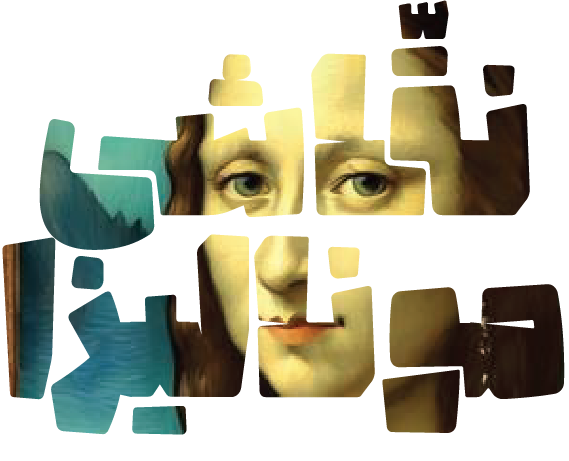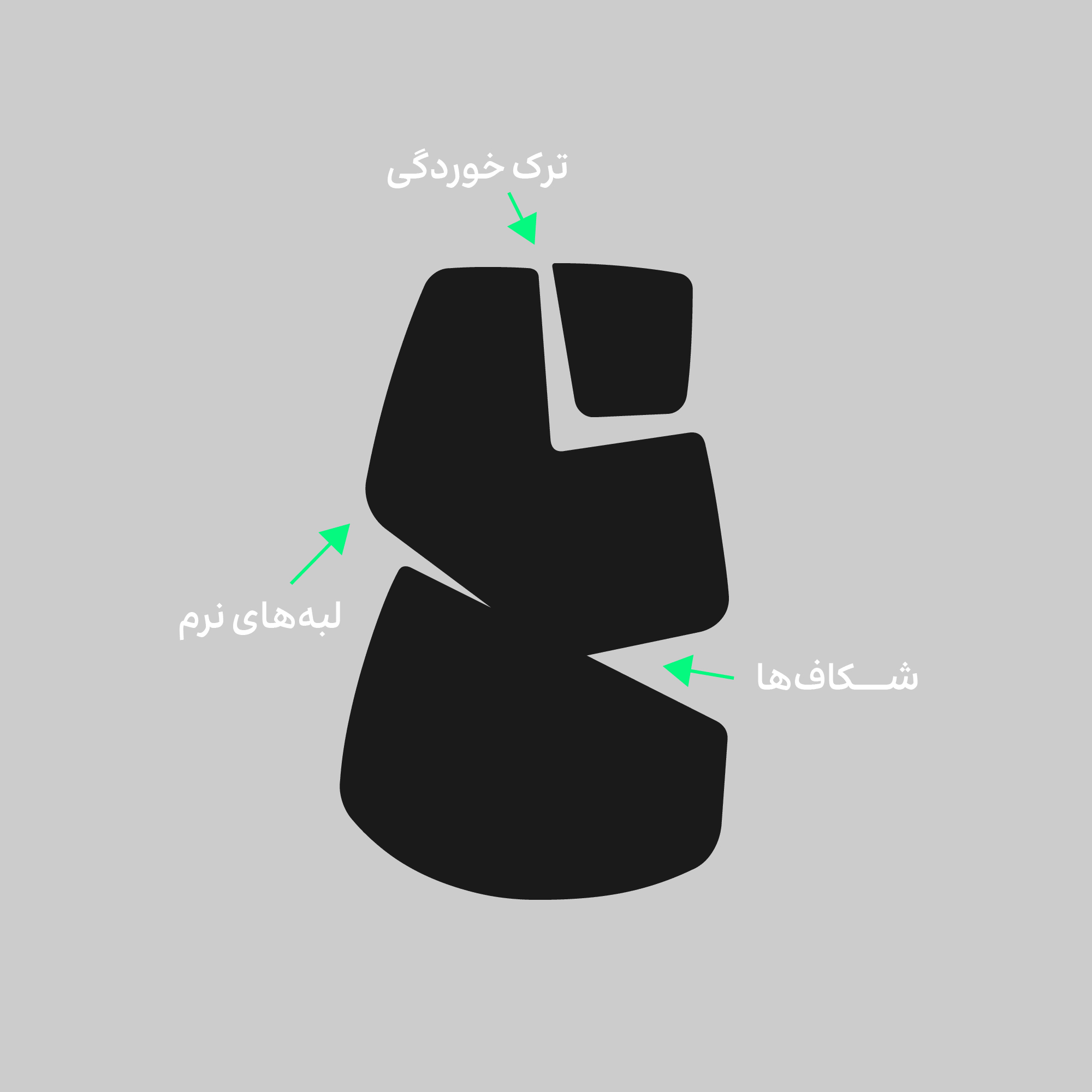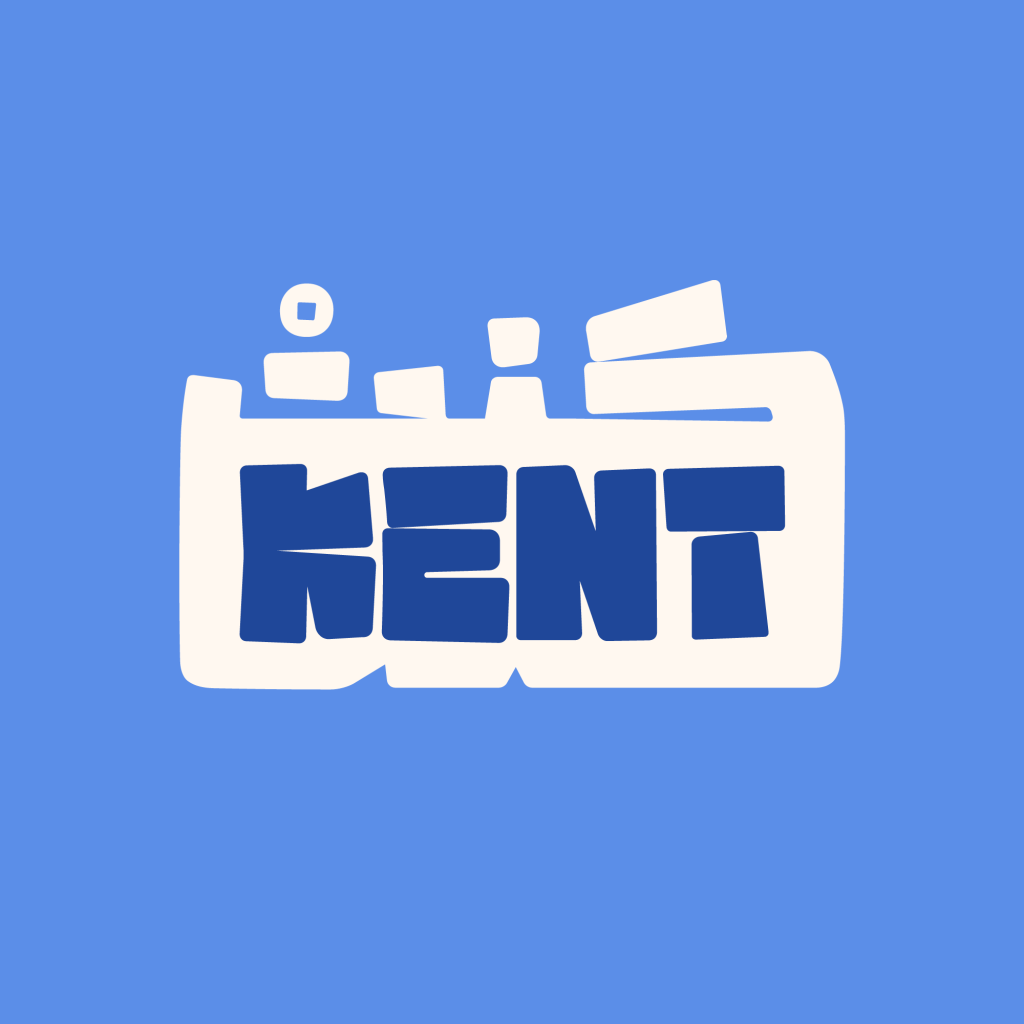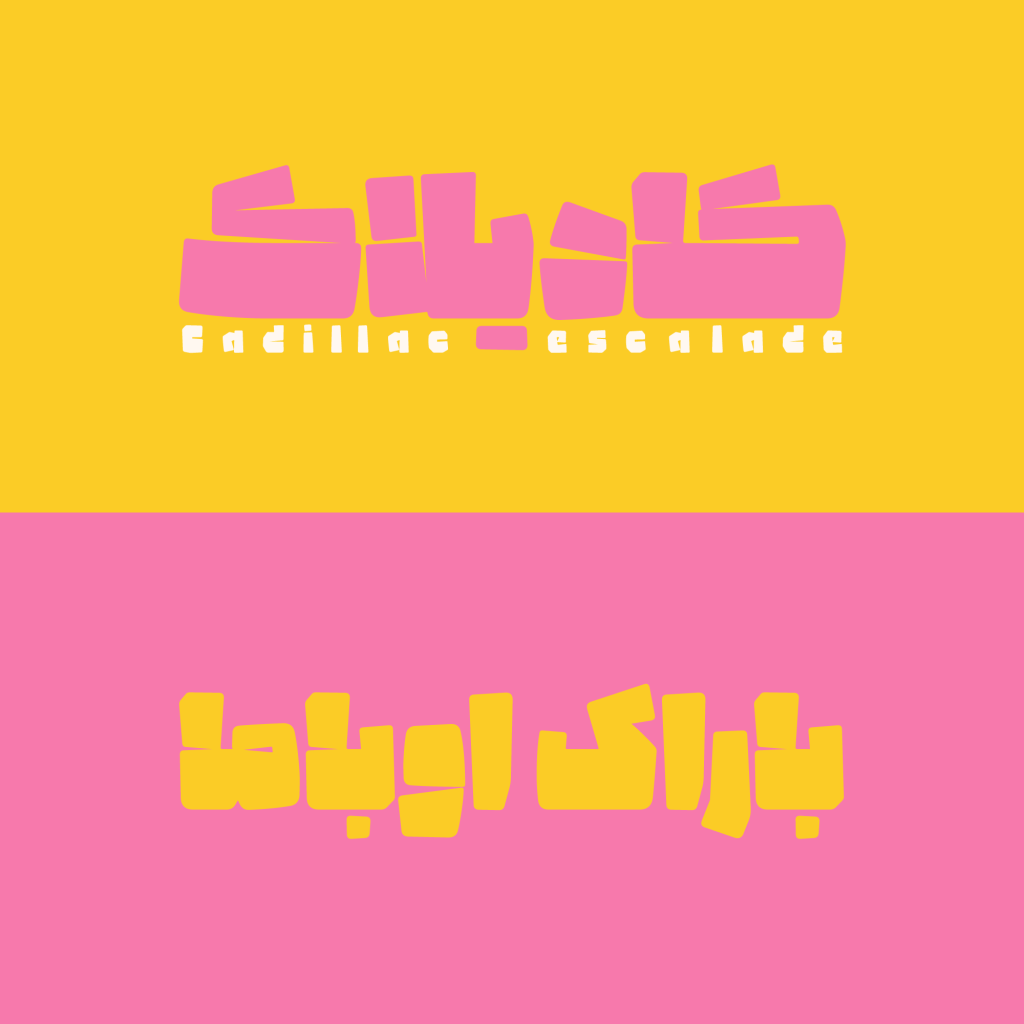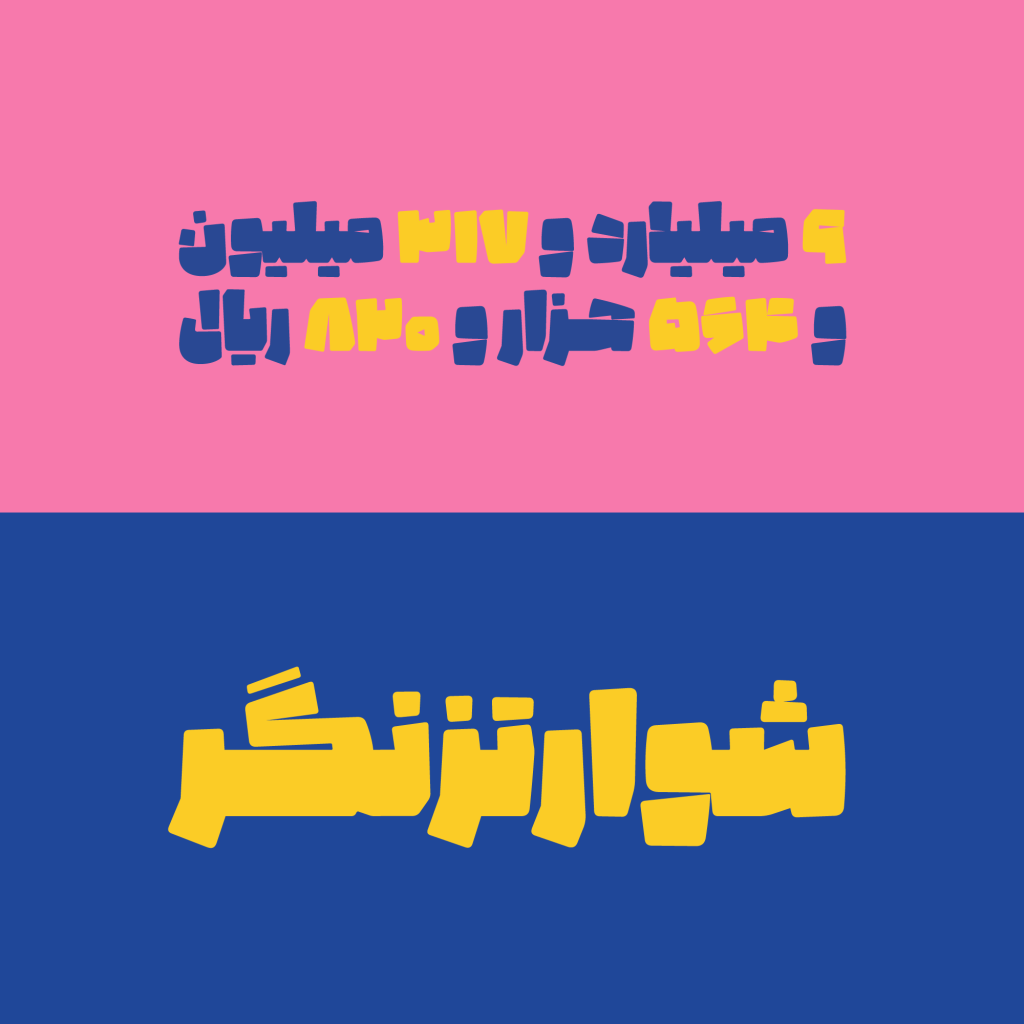
فونت پتک – قلمی فوق العاده نمایشی
فونت پتک قلمی مناسب عناوین و تیتر های تبلیغاتی با ویژگی نمایشی جهت جذب نگاه خوانندگان و بینندگان خود است. مطمئنا در نگاه اول متوجه شیوه خاص و عیر معمول در طراحی گلیف ها و حروف این فونت می شوید. همچنین اتصالات این گلیف ها که تبعیت از فرم خاص طراحی آن دارد.
به عبارت دیگر گویی با چکش و پتک بر بدنه و اسکلت این قلم نواخته و کوبیه شده که نام آن برگرفته از این چکش کاری بر بدنه آن است. تصویری خاص و ایده ای نو در دل طراحی این تایپ فیس وجود دارد. این قلم از دسته پرضخامت و حجیم در سطح به شمار می رود و ریخت واسکلت خاص نگاه هر بیننده ای را به خودت جذب می کند.
پتک مناسب عناوین و تیتر های خاص
بی شک کاربرد اصلی این تایپ فیس برای عناوین کوتاه تبلیغاتی و تیتر های بازاریابی در هر محیطی از مطبوعات و نشریات گرفته تا دنیای وب و شبکه های اجتماعی . شکل بسیار خاص طراحی گلیف ها و حروف سبب تمرکز و دقت مخاطبین و جذب نگاه آنان به این قلم می شود. علی الخصوص که دارای حجم و ضخامتی بالاست که ویژگی نمایشی بودن آن را دو چندان می نماید.
با اندکی تامل می توان دریفت در فونت پتک تغییراتی مثل کم شدن فضای بین حروف و چشمها، برهمزدن یکنواختی در ضخامتها و شکستگیهای اتفاقی و تغییر در اندازهها فضای متفاوتی و جدیدی را خلق نموده است. تغییراتی نظیر کاهش فضای بین حروف و چشمها، برهمزدن یکنواختی در ضخامتها و شکستگیهای اتفاقی و تغییر در اندازهها فضای متفاوتی را در این فونت بوجود آورده است.
این قلم از خانواده هندسی با لبههای نرم حروف به همراه شکستگیهاو چکش کاری های خود ایجاد شده است. گویی از کنار هم قرار گرفتن تکه های کوچک و درشت ساخته شده است از نقطه نظر شباهت و هم خانوادگی به خصوص ظاهری خاص می توان پتک را شبیه به فونت والهالا دانست. این قلم هم بسیار خاص و مناسب عناوین کوتاه و تیتر های تبلیغاتی است.
پتک و پشتیبانی از ترکیبات جایگزین
دارا بودن تایپ فیس های فارسی از ویژگی حروف جاگزین مزیتی سودمند و پرفایده است که تنوع و زیبایی را در طراحیدو چندان می کند. پتک نیز از این قابلیت پشتیبانی می کند .وجود ترکیب های متنوع در فونت های نمایشی برای خلق عبارت متفاوت امری لازم است. که در تصاویر زیر نمونه هایی از آن را می توانید ببینید.
پتک دارای شخصیتی پر انرژی و پویا است که با پشتیبانی از 5 قابلیت های بالای خود را به نمایش می گذارد . شما عزیزان می توانید تصاویر زیبا و نمونه این قلم خاص و ویژه را مشاهده کنید.